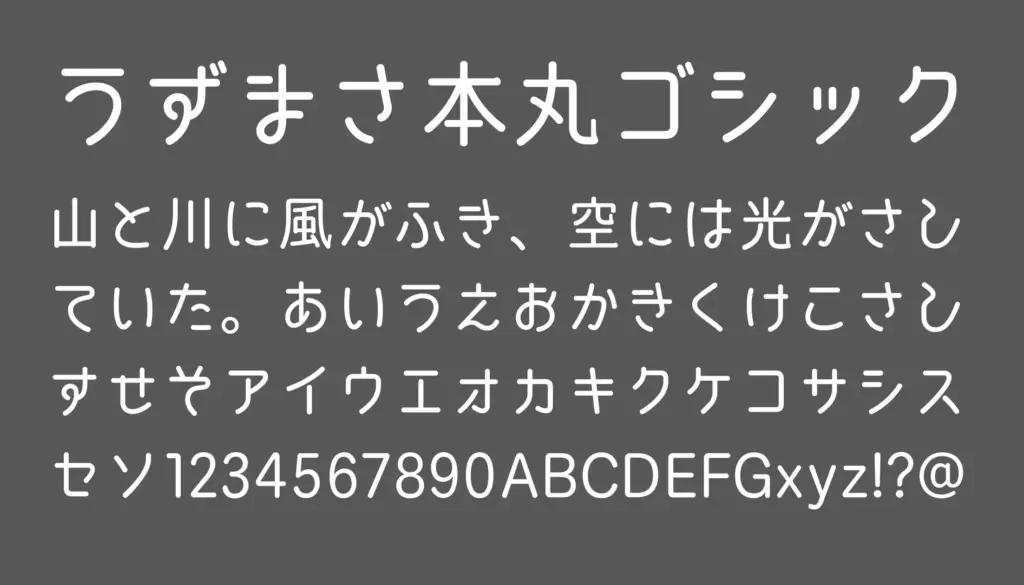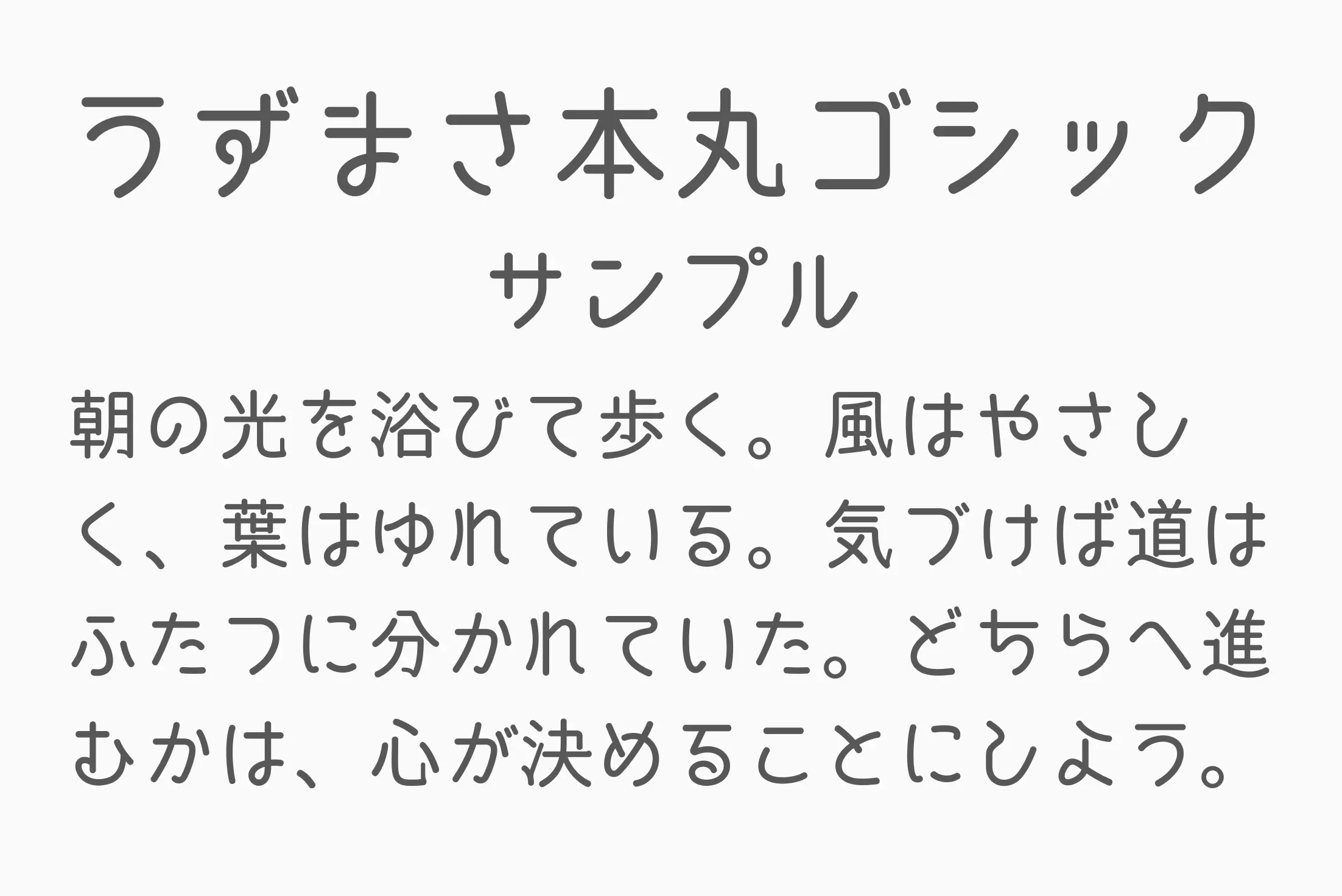
やわらかい丸みとシンプルな線を特徴とするゴシック体フォントです。古風な情緒を感じさせつつ、現代的なミニマルデザインにも調和するため、和風テイストの広告や書籍タイトル、Webデザインなど幅広いシーンで活用できます。丸みを帯びたフォルムは親しみやすく、柔らかさと可読性を兼ね備えています。
うずまさ本丸ゴシック